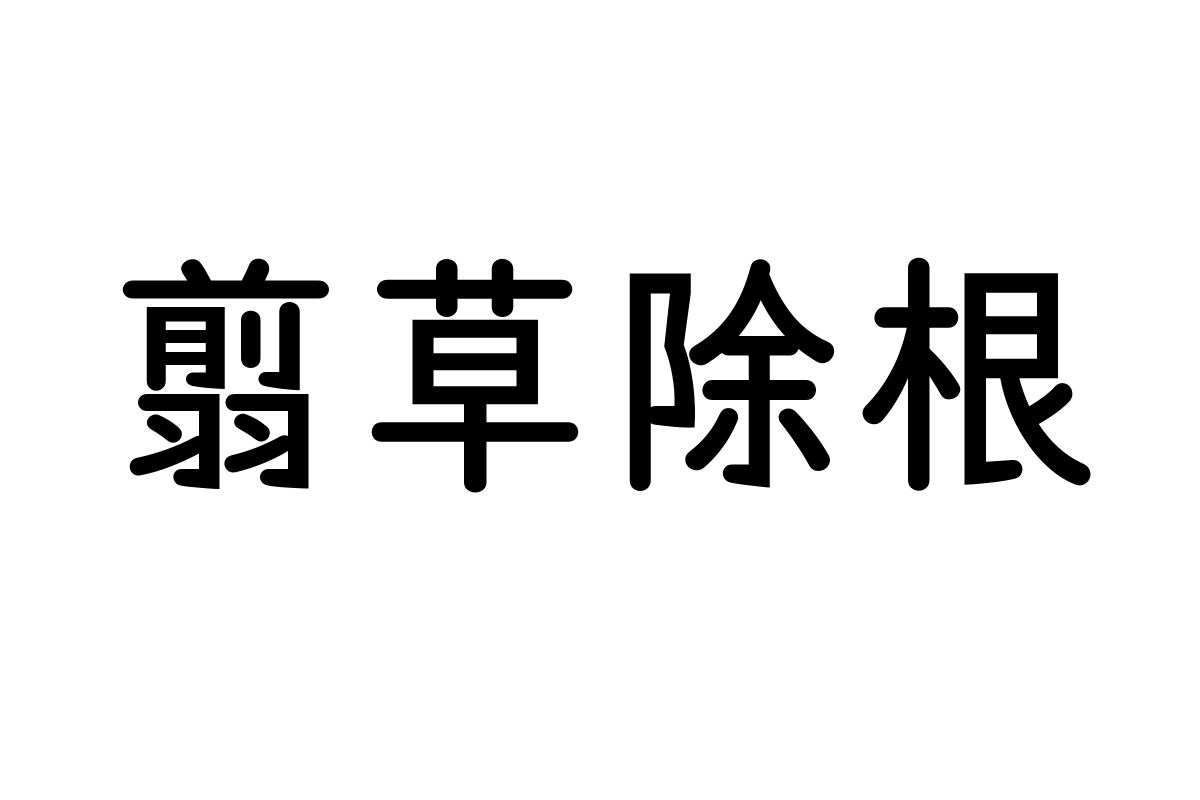
汉仪懒美美是一款现代感十足的中文字体,它以其简洁、时尚的外观赢得了广大用户的喜爱。这款字体采用了独特的设计手法,将传统汉字与现代元素相结合,创造出一种既具有文化底蕴又不失时尚感的字体风格。
汉仪懒美美字体的特点在于其线条流畅、结构紧凑,给人一种轻松自在的感觉。它的笔画粗细适中,既不过于粗犷也不过于细腻,使得整体看起来既美观又易于阅读。同时,汉仪懒美美字体还注重细节的处理,如字间距、行距等都经过精心调整,使得整个字体看起来更加协调、美观。
除了外观上的美感,汉仪懒美美字体在实用性方面也表现出色。这款字体适用于各种场合,无论是用于书籍、杂志、海报还是网页设计,都能展现出其独特的魅力。此外,汉仪懒美美字体还具有较高的可读性,无论是大字还是小字,都能保持清晰易读的效果,满足不同用户的需求。
总之,汉仪懒美美字体是一款集美观与实用于一身的优秀字体,无论是个人使用还是商业用途,都值得一试。
汉仪懒美美